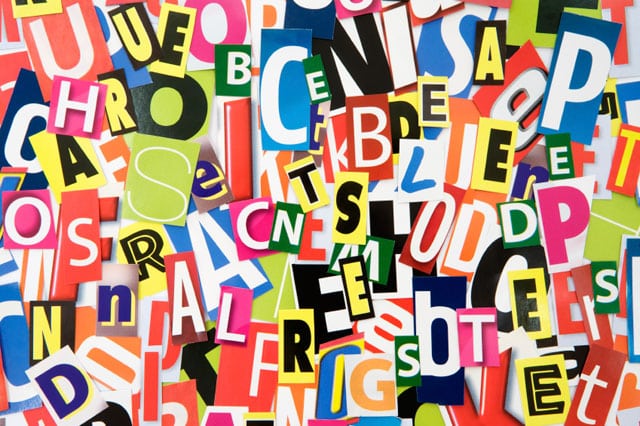
Hoy en nuestro blog Diario THC vamos a volver a hablar de tipos de letras. En realidad lo hacemos con una reflexión sobre todo para todos aquellos que acaban de llegar al mundo del diseño, porque a veces innovar en tipografÃa es sinónimo de aburrir al lector. En realidad las tipografÃas se utilizan para todo, para una campaña publicitaria puntual, para un periódico, para los logotipos y hasta para la web. Y aunque depende del uso que le vamos a dar hoy partimos de la base de que es preferible una vieja tipografÃa y eficiente que una actual y pasajera.
Claro que por ejemplo dentro de un cartel que va a durar como mucho una semana antes de un evento, puede ser una excepción, pero la norma se aplica a todo lo demás, a lo que tiene digamos una «fecha de caducidad» más amplia
Con esto queremos decir que las tipografÃas más clásicas, esas de las que todos tenemos tendencias a escapar porque les parecen poco interesantes, y que a veces nos tientan con tipos como Comic Sans que acaban por distraer al lector si tiene que estar continuamente soportando una letra como esa. ¿La conclusión? Simplemente es preferible un tipo clásico y que funcione que uno innovador que nos chafe el proyecto.